说起少女字体你的脑海里第一个会想到什么?你的脑海里是否是读书时班上腼腆可爱、成绩优异的那个女孩笔下书写的字体,字迹清秀、娇俏可爱,流畅工整如沐春风。又或者是赫赫有名的华康少女体。No no!今天要说的都不是这些,今天小编要先给大家隆重介绍一个“身怀十八般武艺”、拥有八色鸟魅力的的宝藏少女。
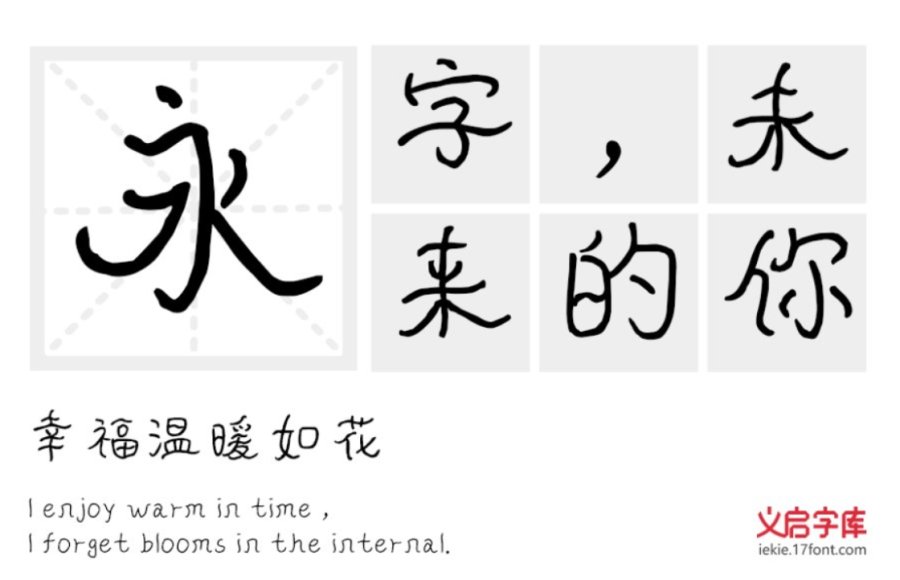
这是一位叫做“义启宝藏少女”的从这张字体图片可以看到这位“少女”不羁的个性特征,不拘泥于这个世界束缚的决心,瞧这舒适自然、淡定自若的神态。抽象的线条传递出“少女”的艺术细胞,傲娇地展现自己那藏也藏不住才华。“少女”在传递艺术性的同时保持了字体的清晰度,散发自己的闪光点。在logo、广告、动漫、影视综艺等领域都能展现光芒。宝藏女孩,浑身是宝,哪哪都好~
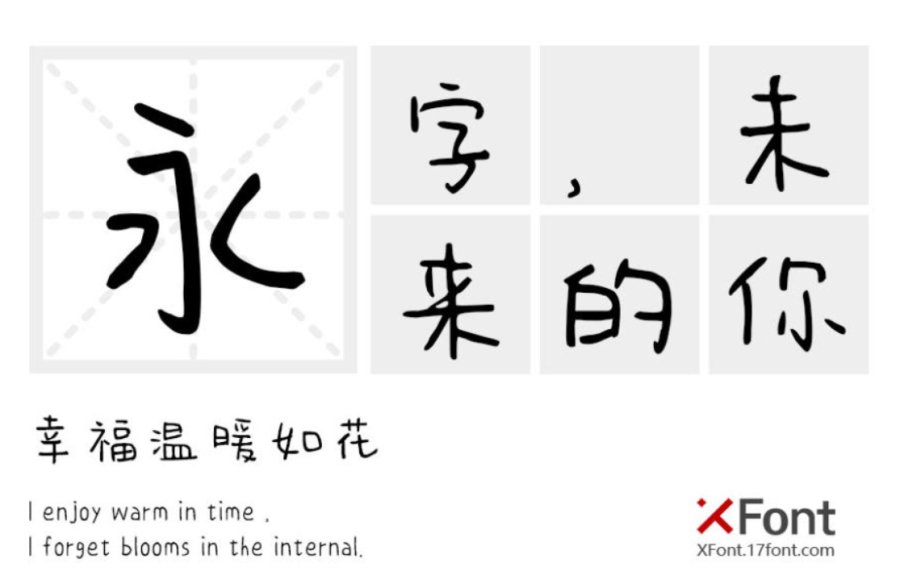
接下来这是一位“宇宙无敌美少女”对你眨着水汪汪的大眼睛,电力可谓是一万伏特。作为“宇宙无敌美少女”当然要保持袅娜的身姿,所以字体的字形端正干练易于识别字体。俏皮可爱的气质在线条的弧线呈现上展露无遗。起笔收笔的干脆利落展现出帅气潇洒的别样魅力。适用于书籍、杂志标题及正文、logo、化妆品、服装广告、影视、社交网络的个性化用字等领域。果然是集美貌与智慧于一身“宇宙无敌美少女”。